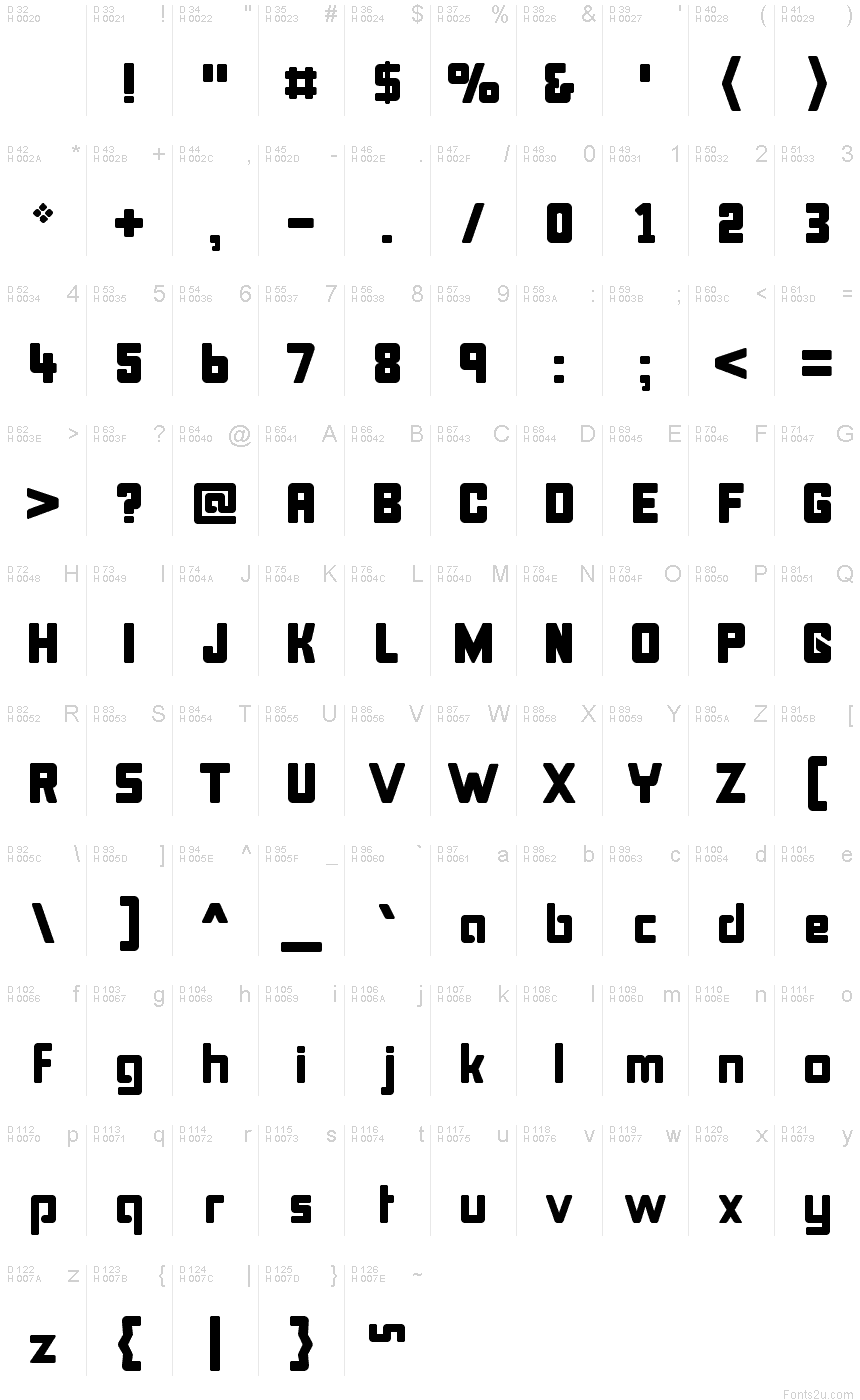
Bonk od GemFonts to darmowy font typu display z masywnymi, miękko zaokrąglonymi literami, które na stronie wybrzmiewają niczym efekt dźwiękowy. Blokowe formy i kwadratowe wnętrza znaków są jednocześnie odważne i pełne energii, nadając nagłówkom zabawny, niemal komiksowy charakter. Zwarta konstrukcja tworzy silny, spójny obraz słowa, który natychmiast przyciąga wzrok, nie sprawiając przy tym wrażenia niechlujnego czy trudnego w odbiorze.
Bonk świetnie sprawdzi się na okładkach książek dla dzieci, w logotypach komiksów, tytułach gier, opakowaniach zabawek, na plakatach, naklejkach oraz wyrazistych grafikach do mediów społecznościowych. Ten bezpłatny font najlepiej prezentuje się w dużym rozmiarze, gdzie jego grube kreski i kompaktowy rytm naprawdę „wyskakują” z ekranu. W mniejszych tekstach warto łączyć go z prostym krojem bezszeryfowym, aby zachować równowagę i czytelność projektu.